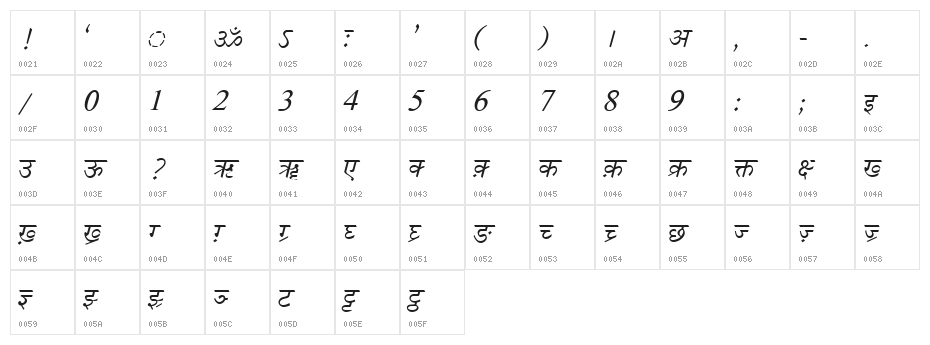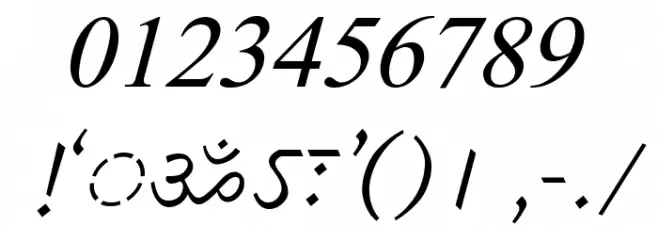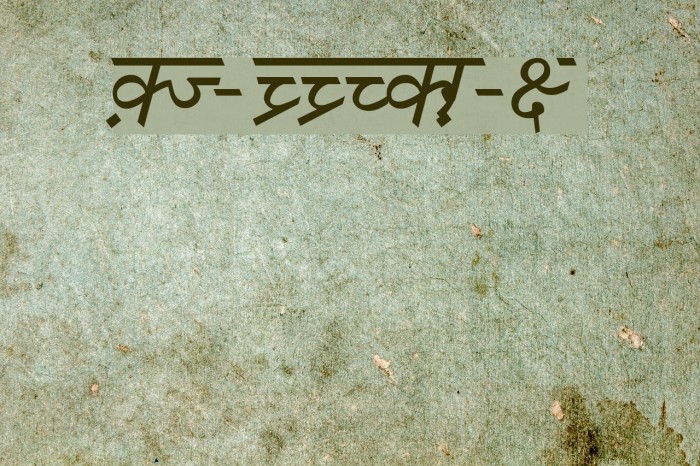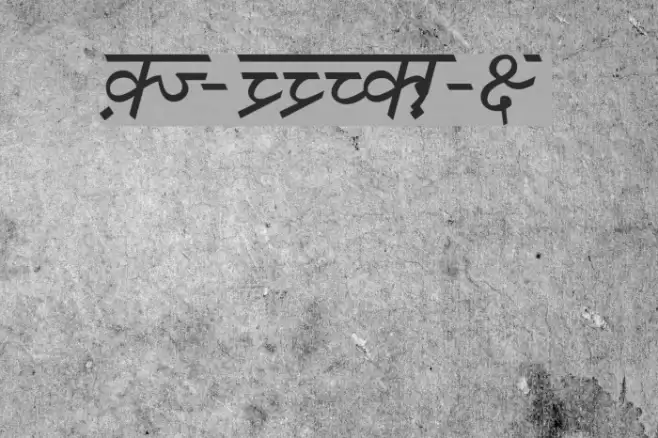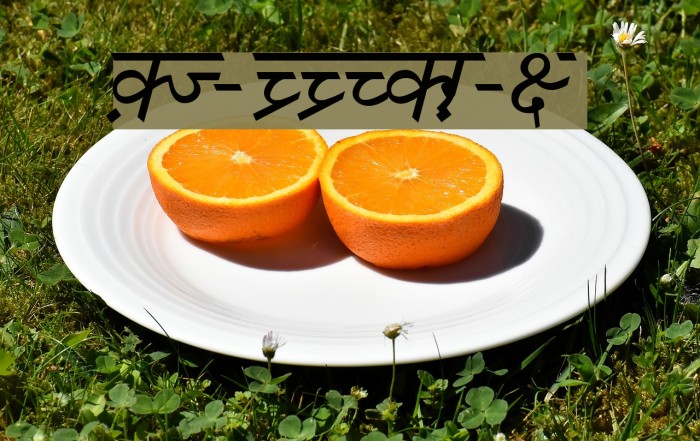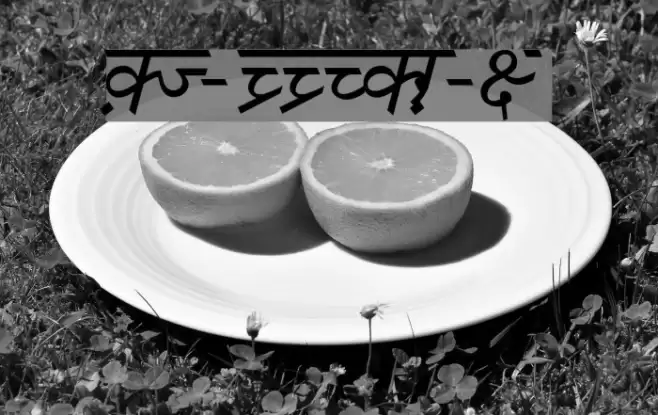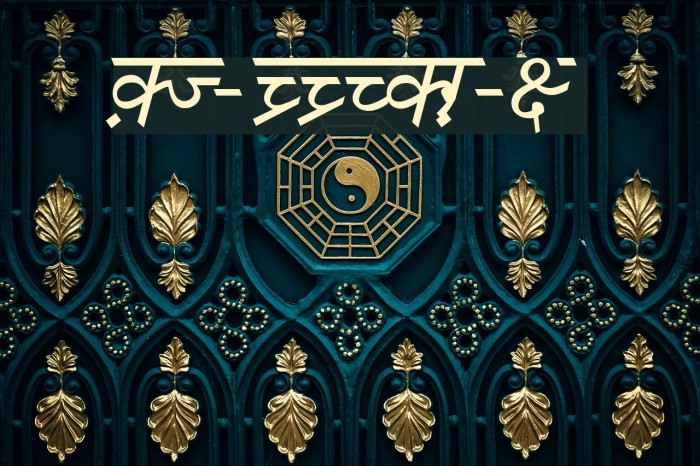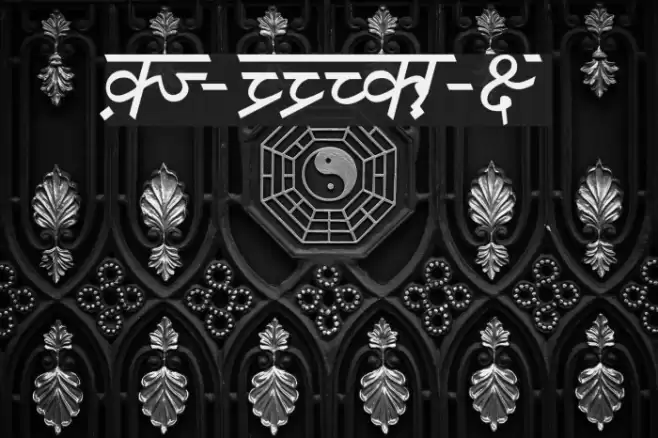
DV-TTSurekhEN-Italic Font
| Gesamtstil | Elegant, Classic |
| Anwendungsfall | Invitations, Branding, Editorial Design |
| Vorgeschlagene Projekte | Ideal for use in formal invitations, elegant branding, and sophisticated editorial design. |